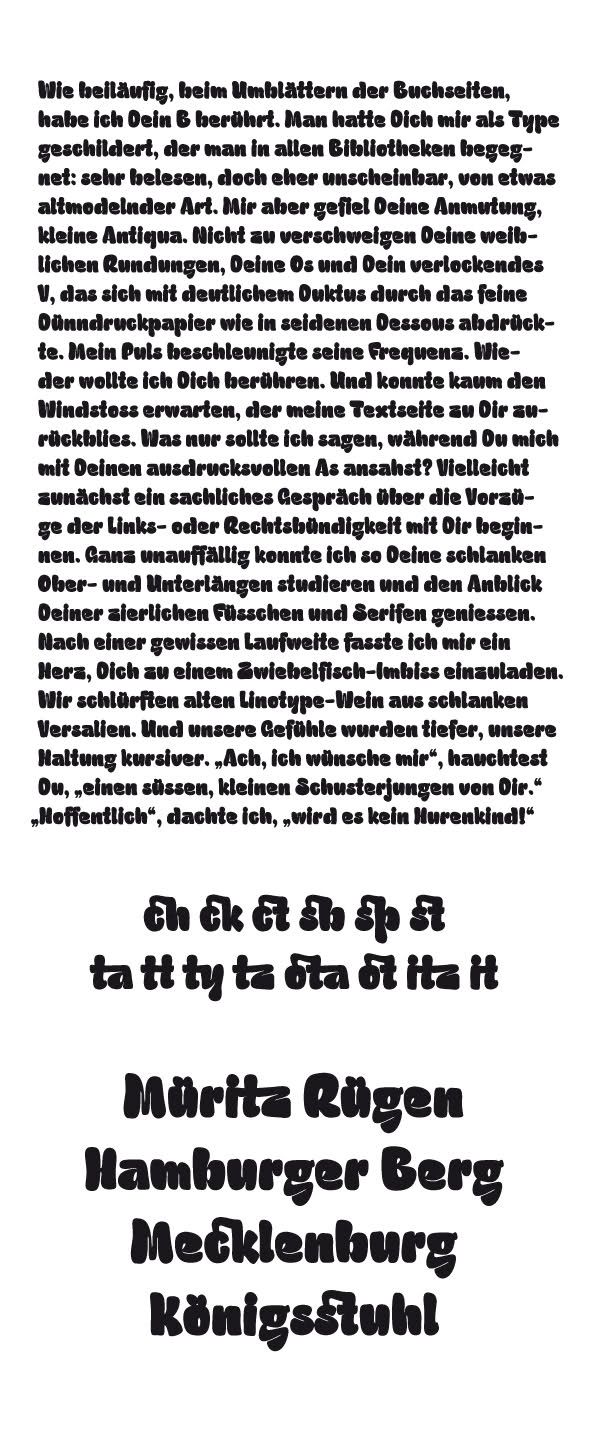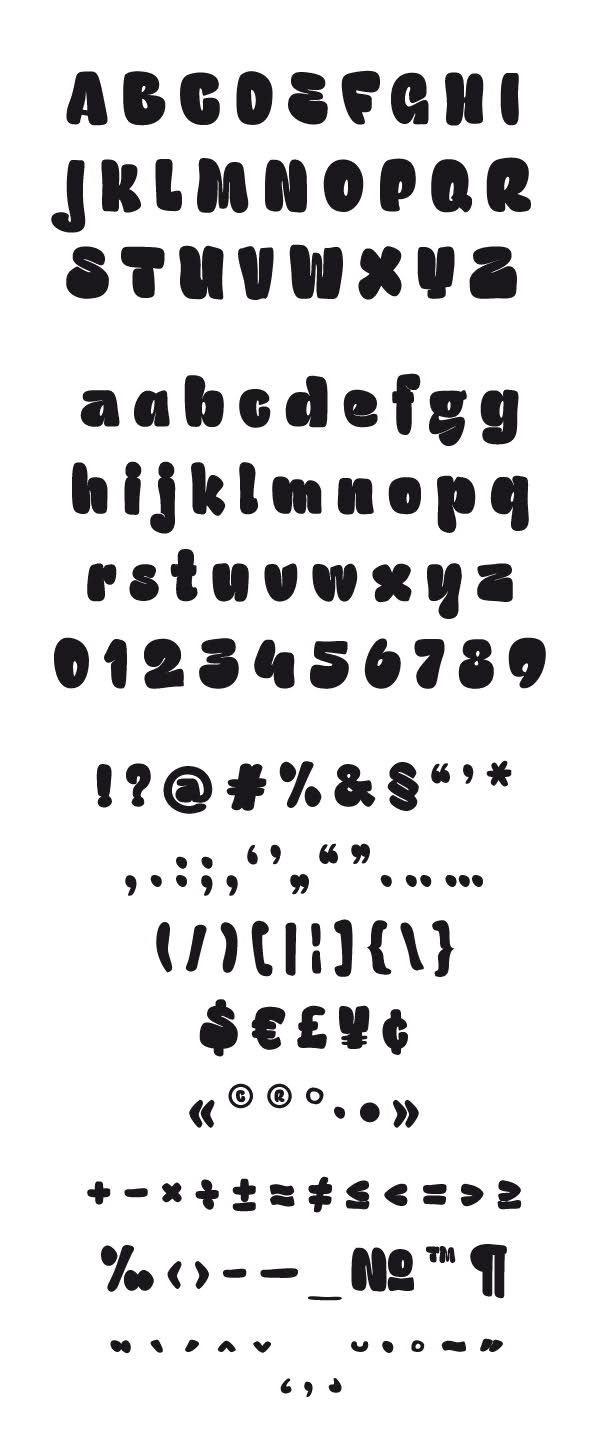
Schriftentwurf Atmosphere ... Kritik und los
So langsam steh ich auf dem Schlauch und werde ein wenig blind. Bitte feuert Kritiken oder ähnliches zu meiner Schrift raus. Ansonsten denke ich nachher noch, dass ich damit schon zu MyFonts gehen kann.
Ich denke einige Versalien können noch ein wenig schlanker werden, die sind mir im Fließtext doch noch ein wenig zu dunkel, das "Z" zum Beispiel.
Auf den ersten Blick sind 'O' 'D' 'A' 'R' 'u' 'ü' und halt das 'Z' das du gemeint hast zu dunkel.
Weiß allerdings immer noch nicht ob sie mir gefällt. Auf der einen Seite hat sie was. Auf der anderen sind mir die Formen teilweise zu wahllos :?
…aber wie ich dich kenne bekommst Du noch eine gute Richtung rein. hast du mal probiert mit mehr »sharp cuts« – heißen die so? – zu arbeiten. Meine das was du bei T, j, f oder 1 benutzt.
Auf der einen Seite hat sie was. Auf der anderen sind mir die Formen teilweise zu wahllos :?
halb/halb ... Aber daher teilweise auch meine Zweifel. Die Schrift steht „gerade“ und hat kursive Einflüsse. Ich glaub, ich könnte viele kleine Makel beheben, wenn sie eine richtige Kursive ist ... oh man. :wink:
Alle möglichen Ligaturen, aber kein ß?
Das D ist nicht als solches wahrnehmbar, ich habe im Text immer erst einmal O gelesen.
Was mir grad noch auffällt: Wenn es ein Grundprinzip deiner Schrifft ist, dass aneinanderstoßende Formen durch eine negative Linie getrennt werden, wie das bei vielen Buchstaben der Fall ist (etwa bei e oder g), dann sollten Bei i und j die Punkte auch nicht mit dem Stamm verschmelzen.
Da mußte ich jetzt aber 3mal lesen, was du meintest. Probier ich mal aus.
@ Pachulke ... Die O,D Problematik ist mir bekannt, obwohl das D in dem Fall der Übeltäter ist.
s, z, e etc. laufen mir zu stark zu (ich seh dann nur noch Kleckse), bei u, n, m hingegen funktioniert's doch.
War doch absolut verständlich formuliert ... ähm ja ... Beim ß isses übrigens das Selbe. Das ist inkonsequent, wenn Formen einmal weich zusammenschmelzen und einmal relativ brutal getrennt werden, an der Stelle würde ich mir mehr Prinzipientreue wünschen.
War doch absolut verständlich formuliert ... ähm ja ... Beim ß isses übrigens das Selbe.
War es auch, deswegen meinte ich ja am Anfang ich bin ein wenig blind geworden und sehe so Fehler überhaupt nicht mehr. Hab mir an einigen Stellen diese Gedanken bis jetzt überhaupt noch nicht gemacht.
Erstmal: Eine lebendige und locker-freche Schrift. Gefällt mir gut. Bravo.
Ergänzend zu den Anmerkungen oben, nur dies: Stichwort Ligaturen. Ich würde das Gewicht nicht auf die manirierten Ligaturen wie ch, ck, ct etc. legen, sondern bei dieser Schrift eher auf Alternativen wie in der unteren Zeile hoffen. Dabei fehlen einige wichtige noch (oder sind die nicht abgebildet?): ff, fi, ll etc.
Außerdem sollte man Ligaturen einbauen, die im englischen Satz gebräuchlich sind. Würde den Einsatzgebiet erhöhen. Habe jetzt keinen Beleg dafür, aber ich bin mir sicher, dass im Englischen andere Ligaturen gebräuchlich sind wie z.B. im Deutschen. Ich würde mich bei der Auswahl der Ligaturen an z.B, der Bello orientieren.
Mich irritiert das Fließtext-Sample ein wenig, denn diese Schrift kann ja wohl nur in der Displayanwendung eingesetzt werden. Da würde ich eher solche Beispiele anführen.
das ich die schrift suuuper finde hatte ich ja schon geschrieben. :biglove:
nur mal so die voransicht und nicht auf das pdf geschielt würde ich sagen:
D und O müssen sich mehr unterscheiden.
das Z hätte ich gern andersherum, also mit dem schwerpunkt oben, gesehen.
das J passt nicht ganz rein, bei einigen fehlen diese tintenfallen, also einkerbungen. (K, L, 4, 5, 7 ...) oder sehe ich die in der voransicht nur nicht?
die i-punkte würden mir besser gefallen wenn sie nicht mit dem buchstaben verschmelzen.
so, jetzt habe ich mir doch mal schnell das pdf gezogen und sehe es fehlen bei einigen buchstaben diese 'cuts'. beim T der cut ist ja super, aber wieso ist er dann nicht bei den anderen zeichen? ich bin kein typedesigner, aber sowas finde ich dann immer etwas wahllos, mehr kontinuität würde ich mir da wünschen.
oder du machst zwei fonts daraus, einen für kleine schriftgrade und einen für displayanwendungen. ich könnte mir vorstellen wenn du das mit den cuts bei allen zeichen durchziehst, wirkt das am ende auch etwas störend. bei den kleinbuchstaben sind die cuts auch öfters zu finden, dort sind sie teilweise aber sehr unterschiedlich in ihrer größe. siehe: t, j, f. das macht sich auch im fließtext bemerkbar, e, z, g fallen duch ihre cuts heraus und andere zeichen hingegen wirken zu dunkel.
Tolle Schrift.
Allerdings würde ich bei der Präsentation unbedingt den „Mengentext“ weglassen. Da kommt der Font eher schlecht rüber. Erst so ist mir auch eine Schwäche der „Atmosphere" aufgefallen: Die vertikalen Formen „explodieren“ praktisch, aber die Schrift müsste eigentlich auch mehr um die Schriftlinie herum „tanzen“. Vielleicht sehe ich da aber auch einen ganz anderen Font …
Ein paar farbige, peppige Beispiele würden zudem besser kommen. Mit bunten Konturen und Füllungen zu spielen wäre vielleicht ganz lustig.